Trong thiết kế kiến trúc và đồ họa, các bộ Handwriting font Việt hóa mang đến nét chữ thủ công đầy cảm hứng, giúp xóa bỏ sự khô cứng của các kiểu chữ in ấn công nghiệp. Với nhịp điệu tự nhiên và đường nét mềm mại, dòng phông chữ này thường được ưu tiên để tạo dấu ấn cá nhân cho bộ nhận diện homestay, quán cafe hoặc trang trí không gian sống hiện đại.
Đặc điểm thẩm mỹ của các dòng Handwriting font Việt hóa
Nét lôi cuốn đặc trưng của phông chữ Handwriting nằm ở sự biến thiên linh hoạt của các nét thanh mảnh và độ dày không đồng nhất, mô phỏng sinh động các vệt mực của bút tay. Việc sử dụng phiên bản Handwriting font Việt hóa free giúp người dùng giải quyết triệt để tình trạng lỗi dấu thanh, đảm bảo các ký tự đặc biệt như “đ, ă, ơ” phối hợp hài hòa với cấu trúc chữ gốc. Điều này mang lại sự chuyên nghiệp, giúp bản thiết kế giữ được vẻ đẹp phóng khoáng nhưng vẫn rất chỉn chu và dễ đọc.
Bên cạnh yếu tố hình khối, Handwriting Việt hóa còn đóng vai trò quan trọng trong việc cân bằng thị giác cho không gian. Trong kiến trúc, những nét chữ mềm mại này thường được dùng để đối trọng với sự góc cạnh của các khối nhà lắp ghép hay văn phòng container, tạo nên một tổng thể hài hòa và giàu cảm xúc. Đây là lựa chọn linh hoạt để thể hiện cá tính riêng, từ phong cách thanh lịch, sang trọng đến mộc mạc, phá cách tùy theo yêu cầu của từng dự án cụ thể.
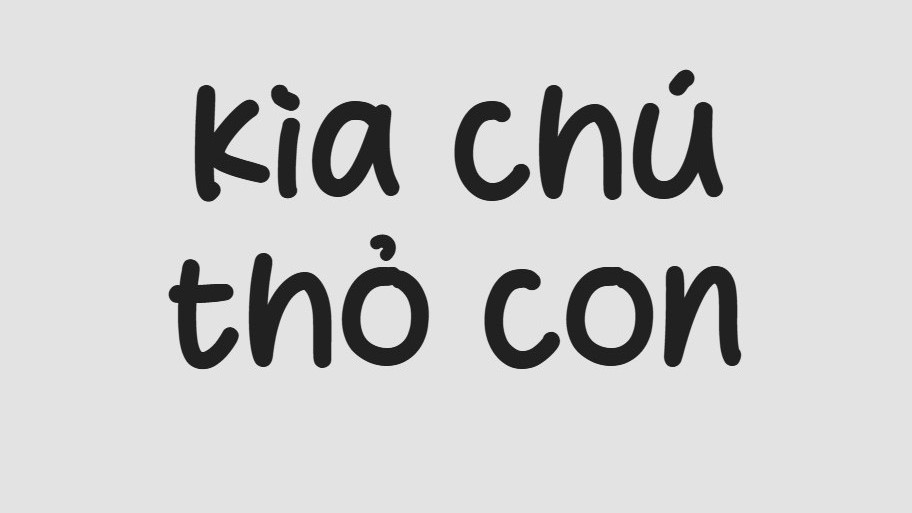
| Mục đích phù hợp | Logo, tiêu đề poster, thiệp mời, decor |
Lời khuyên thiết kế: Khi sử dụng font chữ Handwriting Việt hóa, bạn nên phối hợp chúng cùng một phông chữ không chân (Sans-serif) tối giản cho phần nội dung chi tiết. Sự tương phản giữa tiêu đề viết tay bay bổng và phần văn bản gọn gàng sẽ giúp thông tin chính trở nên nổi bật và chuyên nghiệp hơn.
03 Ứng dụng font việt hóa Handwriting vào thực tế kiến trúc
Nhờ diện mạo giàu tính thẩm mỹ và cá tính riêng, bộ phông chữ này mang lại giá trị cao trong khâu trang trí và quảng bá các công trình hiện đại:
- Hệ thống nhận diện cho Homestay: Những nét chữ viết tay rất ăn ý khi xuất hiện trên biển hiệu gỗ hoặc mica gương tại các khu nhà lắp ghép nghỉ dưỡng. Font chữ này giúp không gian toát lên vẻ thư thái, thu hút du khách yêu thích phong cách sống xanh.
- Trang trí không gian nội thất: Bạn có thể dùng font này để làm tranh quotes trang trí hoặc cắt chữ nổi đèn neon tại phòng khách, khu vực sảnh chờ nhằm tạo điểm nhấn đầy lôi cuốn và khơi gợi cảm hứng cho người sử dụng không gian.
- Thiết kế hồ sơ năng lực dự án: Sử dụng font chữ Handwriting Việt hóa cho các lời nhắn gửi hoặc lời tựa trong hồ sơ giúp thể hiện sự tận tâm và phong cách làm việc chuyên nghiệp, gần gũi của đơn vị kiến tạo đối với khách hàng.
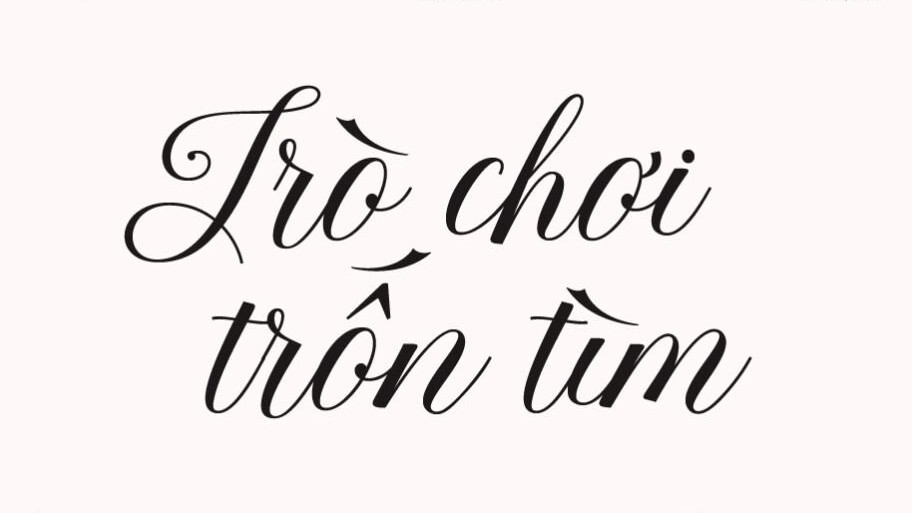
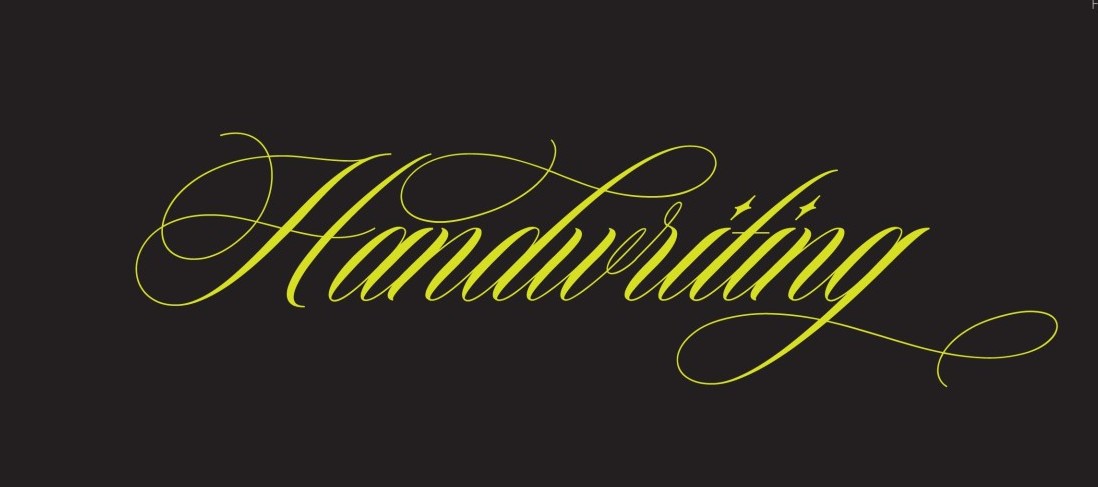
03 Lưu ý kỹ thuật để bố cục Handwriting Việt hóa chuyên nghiệp
Để khai thác hiệu quả vẻ đẹp của dòng font đặc thù này mà không làm giảm tính chuyên nghiệp của bản thiết kế, bạn nên lưu tâm một số kinh nghiệm sau:
- Kiểm soát khả năng đọc hiểu: Do nét chữ viết tay thường có nhiều chi tiết uốn lượn, bạn nên ưu tiên sử dụng cho các tiêu đề ngắn hoặc slogan quan trọng. Tránh dùng cho các đoạn văn bản hướng dẫn dài vì dễ gây mỏi mắt cho người đọc.
- Nới rộng khoảng cách dòng: Hãy thiết lập khoảng cách dòng thoáng một chút để các nét móc vươn dài không bị chồng lấn lên nhau, giữ được sự minh bạch cho văn bản khi nhìn từ xa.
- Hạn chế viết hoa toàn bộ: Đặc trưng của font viết tay là sự liên kết nhịp nhàng giữa các chữ cái viết thường. Việc viết hoa toàn bộ cụm từ sẽ làm mất đi nhịp điệu tự nhiên và khiến tiêu đề trở nên thô cứng, thiếu thẩm mỹ.